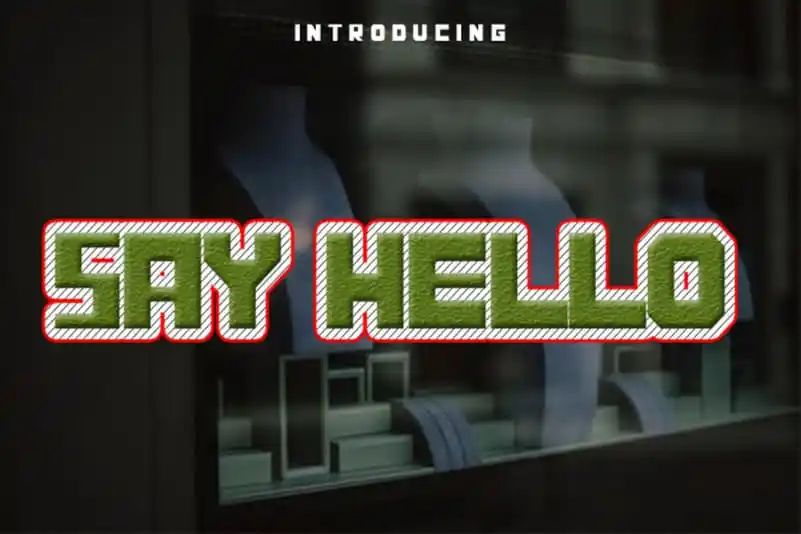
Say Hello Display Font
A Say Hello Display Font é uma linda tipografia sans-serif que mantém seus influentes traços góticos enquanto continua atual e fresco. Este tipo tem versatilidade suficiente para atender a uma ampla variedade de conceitos criativos, desde letras de cabeçalho até materiais de embalagem e cartão-postais, tudo com um toque autêntico que ressalta seu design. Seja para aplicar em logotipos sofisticados ou criar peças de escritório impecáveis, esta fonte é perfeita tanto para projetos profissionais quanto para aqueles momentos inusitadamente criativos. Não importa o tipo de projeto ou a necessidade específica de seu trabalho, a Say Hello Display Font está aqui para ajudar você a expressar suas ideias de forma única e impecável.